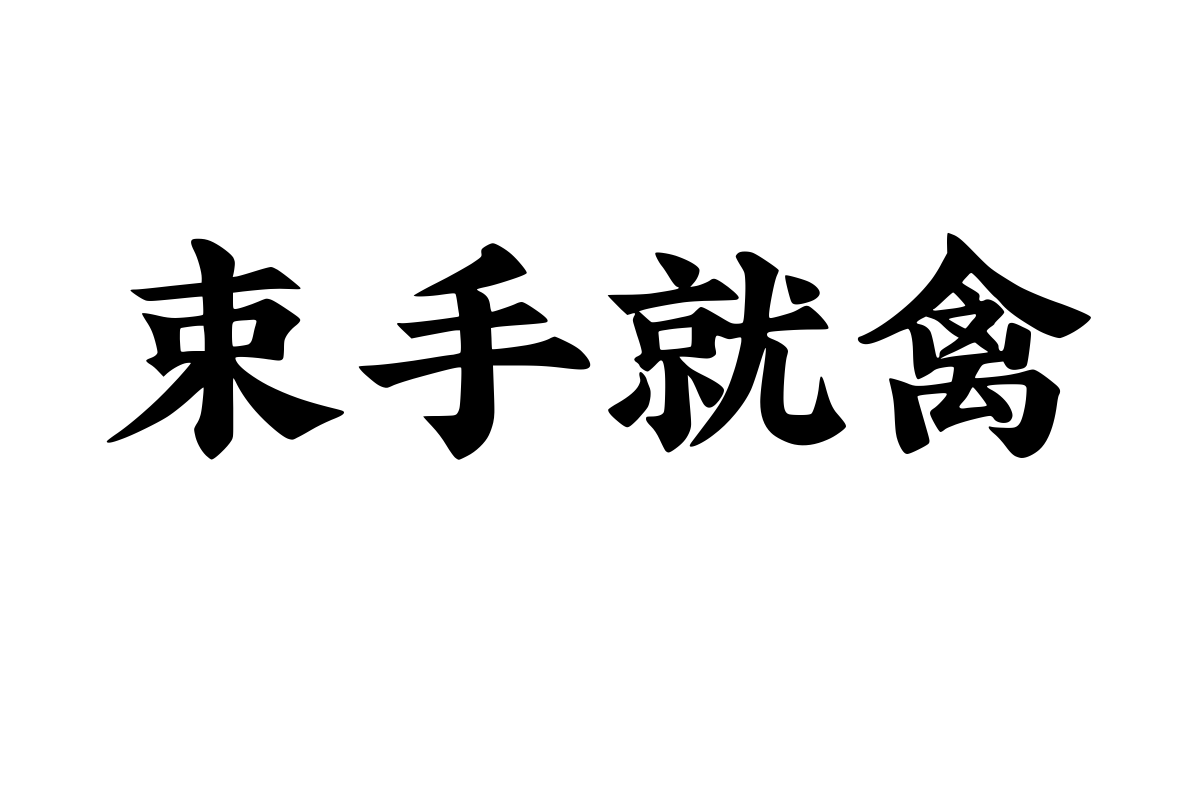
汉呈宋韵杭州字体,是一款具有浓郁中国风的书法字体。它汲取了中国古代书法的精髓,将汉字的笔画、结构和形态进行了巧妙的融合和创新,形成了独特的艺术风格。
这款字体的特点主要体现在以下几个方面:
1. 字形优美:汉呈宋韵杭州字体的字形结构严谨,线条流畅,既有传统的韵味,又不失现代感。无论是书写还是设计,都能给人一种美的享受。
2. 笔触丰富:这款字体的笔画粗细变化丰富,既有粗犷豪放的线条,又有细腻柔和的笔触,给人以强烈的视觉冲击力。
3. 结构独特:汉呈宋韵杭州字体的结构紧凑,每个字的笔画都经过精心设计,使得整个字体既有规律性,又有变化性,给人以新颖的感觉。
4. 文化内涵:这款字体蕴含着丰富的中国传统文化元素,如山水、花鸟、诗词等,让人在欣赏字体的同时,也能感受到中国文化的魅力。
5. 适用性强:汉呈宋韵杭州字体适用于各种场合,无论是用于书法创作、平面设计、广告宣传,还是其他需要展示中国传统文化元素的场合,都能展现出其独特的魅力。
总之,汉呈宋韵杭州字体是一款极具中国特色的书法字体,它以优美的字形、丰富的笔触、独特的结构、深厚的文化内涵和广泛的适用性,深受广大书法爱好者和设计师的喜爱。